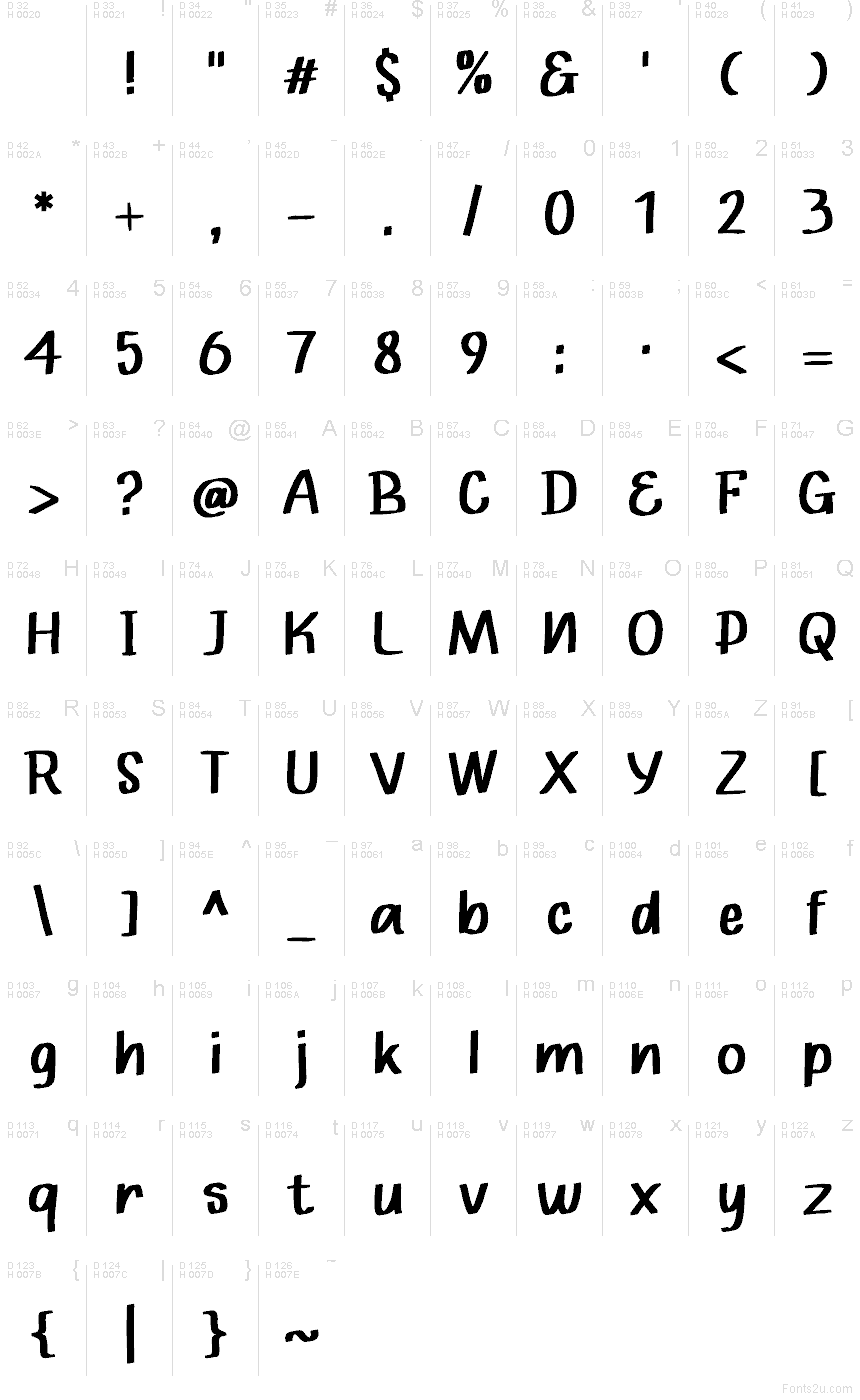
Jumawa Alone
Шрифт Jumawa Alone від Hello Good Studio - це безкоштовний рукописний шрифт із довгими плавними штрихами, заокругленими з'єднаннями та легким нахилом, що надає кожному слову природного та динамічного вигляду. Літери зберігають невимушену, індивідуальну форму, залишаючись при цьому гармонійними в наборі, а відкриті криві та трохи вищі форми роблять написання легким і повітряним.
Jumawa Alone чудово підійде для запрошень, акцентних написів у логотипах, графіки з цитатами, пакування, постів у соцмережах та поліграфії, оскільки цей рукописний стиль виглядає щиро, але не надто офіційно. Цей безкоштовний шрифт також вдало впишеться в брендинг у стилі підпису, заголовки блогів та етикетки товарів, де потрібно додати дизайну нотку індивідуальності.